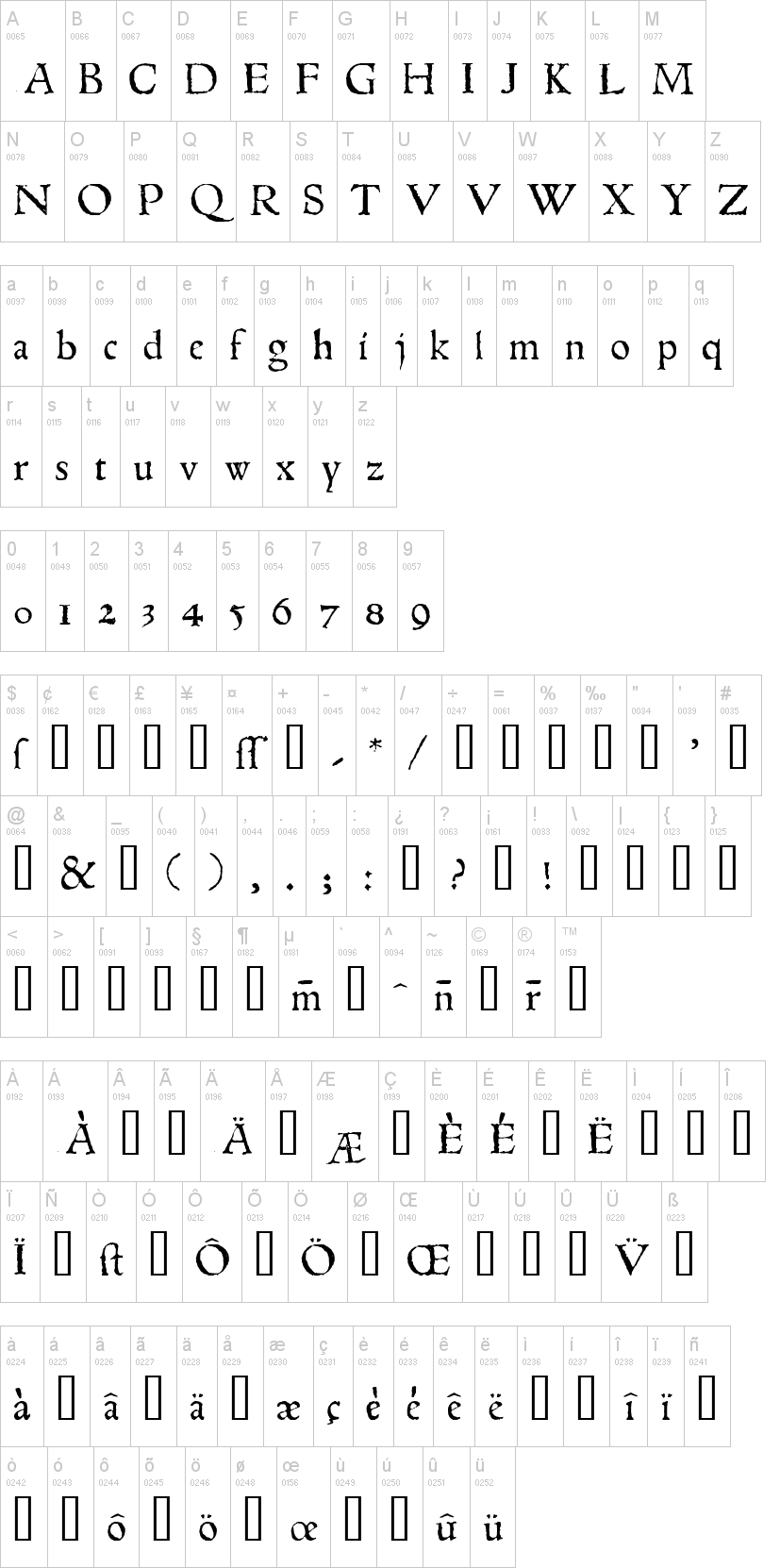
Шрифт 1543 Humane Jenson
Variante de caractères Jenson utilisée en 1543 pour une édition de Vésale. Version 2, expurgée des défauts du fichier bold. Pour usage commercial(15), me contacter.